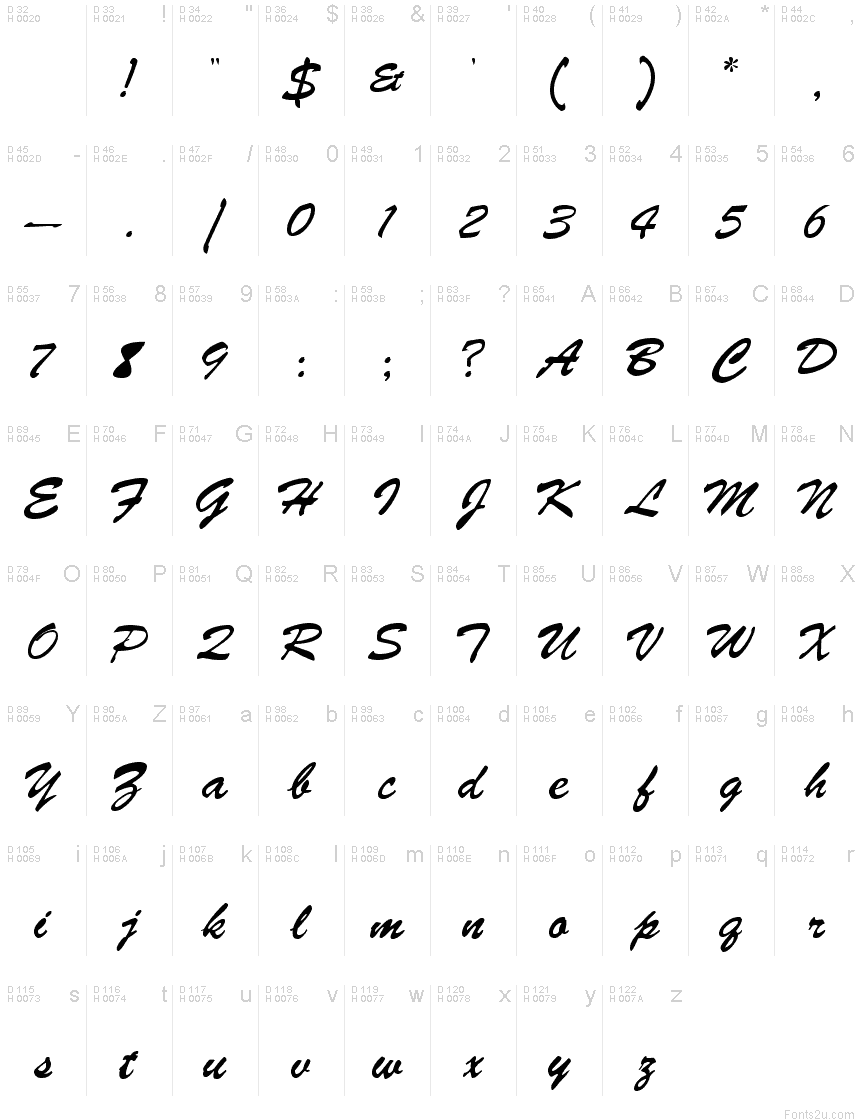
Parquet to bezpłatny font typu brush o swobodnym, odręcznym rytmie i płynnych, pochylonych liniach. Litery łączą się w naturalny sposób, z zaokrągleniami i ostrzejszymi, przypominającymi tusz zakończeniami, co nadaje projektowi dynamiczny, rysowany ręcznie charakter.
Parquet świetnie sprawdza się w logotypach, zaproszeniach, opakowaniach, tytułach plakatów i cytatach w mediach społecznościowych, ponieważ ten styl brush wnosi osobisty, malarski akcent do krótkich tekstów. Ten darmowy font pasuje również do etykiet produktów i dekoracyjnych napisów, gdy zależy Ci na efekcie swobodnym, a jednocześnie starannie wykończonym.